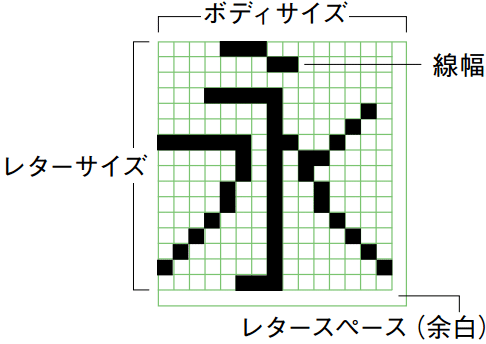
ビットマップフォント
組込み機器の表示に最適化されたドットで構成されたフォントです。OSの有無に関わらず、文字の表示や印刷が可能なため、デジタルサイネージやLED表示器などの掲示板・案内板、スマートウォッチやハンディーターミナルなどのモバイル端末、計測・検査装置やプリンターなど産業用から家電製品まで幅広く採用、特に小さな文字の表示には高い視認性・可読性が評価されています。
ビットマップフォントのメリット
対応環境の広さ
ビットマップフォントは主にバイナリ形式、画像形式でご提供しています。
アウトラインフォントと異なり、フォントデータを描画する仕組が必要ないため、組込み機器でのご利用に最適です。
またウェアラブル端末のような、非常に小さいディスプレイでの表示にも適したフォントサイズを展開しています。
動作の軽量性
ビットマップフォントはデータ容量を小さく抑えています。
ストレージ領域に余裕がないデバイス、ローパワーのCPUで稼働するデバイスなど、リソースに大きな制約がある環境でも文字を表示できます。
豊富な対応言語
日本語のほかに、韓国語、中国語といったアジア圏の言語、英語やスペイン語といったラテン文字を使う言語、その他世界各国の言語に対応するビットマップフォントをご用意しています。
ボディサイズとレターサイズの関係
ビットマップフォントは点で表現されている性質上、フォントのサイズ表記が特殊です。
大きさ(枠)のことをボディサイズ、点(ドット)の情報があるエリアの高さおよび幅をレターサイズと称しております。
• 言語:日本語
• 書体:ゴシック体
• ボディサイズ:16×16(縦×横)、レターサイズ:15×15(縦×横)
• 線幅:1ドット
• レタースペース(余白):下1ドット、右1ドット空き
ビットマップフォント ラインナップ
日本語ビットマップフォントのご提供ラインナップです。
ビットマップフォントラインナップ
ボディサイズ レターサイズ ゴシック 丸ゴシック 明朝 Uni-Type
08x08 08x08 ● - - -
10x10 09x09 ● - - -
12x12 11x11 ● ● ● ●
14x14 13x13 ● - ● ●
16x16 15x15 ● ● ● ●
18x18 17x17 ● ● ● ●
20x20 19x19 ● ● ● ●
22x22 21x21 ● - - -
24x24 23x23 ● ● ● ●
26x26 24x24 ● - - ●
28x28 26x26 ● - ● -
30x30 28x28 ● ● - ●
32x32 30x30 ● ● ● ●
36x36 34x34 ● ● ● ●
40x40 36x36 - - - ●
48x48 44x44 ● - - -
60x60 56x56 - - - ●
64x64 58x58 ● - - -
提供可能サイズ 8dot〜83dot
書体 明朝体、ゴシック体、太ゴシック体、丸ゴシック体など
対応言語 日本語、中国語(簡体字/繁体字)、韓国語、ラテン系言語、ロシア語、ギリシア語など
その他 外字作成、必要な文字サイズの作成が可能
Uni-Type
Uni-Typeはユニバーサルデザインに対応したビットマップフォントです。
漢字とかなの大きさのバランスを調整し、文字から余分な装飾を省くことで視認性、可読性を向上させています。